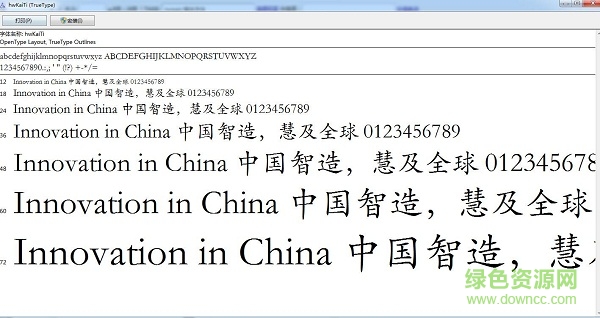
軟件介紹 軟件標簽: hwkaiti 楷體字體 hwkaiti.ttf字體是一款美觀大氣的楷體字體,該字體起筆和收筆分明,結(jié)構(gòu)舒展,柔中帶剛,用于正文排版和包裝設(shè)計,有著不錯的可讀性,歡迎大家前來下載!hwkaiti字體特點這款字體被大量應(yīng)用于報紙、雜志和書籍中的正文,結(jié)構(gòu)秀麗勻稱,筆畫圓潤柔和,可直接用于廣告標語和平面設(shè)計!優(yōu)秀楷體推薦楷體cs-normal普通體 授權(quán):免費軟件 WinAll, WinXP, Win7大小:3.4M語言:中文楷體csregular普通字體是一款規(guī)整大氣的楷書字體,該字體結(jié)構(gòu)瀟灑,筆畫搭配合理,線條流暢大方,雅俗共賞,適用領(lǐng)域廣泛,喜歡的朋友快來下載吧!楷書字體練習(xí)要點掌握好大楷的點畫、結(jié)構(gòu)、布白,做到點畫準確精到下載地址方正小龍楷體ttf 授權(quán):免費軟件 WinAll, WinXP, Win7大?。?.4M語言:中文方正小龍楷體ttf字體是一款端正漂亮的楷書字體,字體線條筆畫流暢,個性鮮明,大氣實用,適用于廣告標語、包裝設(shè)計以及平面設(shè)計等方面,有需要者歡迎下載!創(chuàng)意字體介紹【書同體】在風(fēng)格上有獨到之處,是積幾十年下載地址hwkaiti字體安裝方法方法一:控制面板/字體/文件/安裝新字體;方法二:直接將字體復(fù)制到C:\WINDOWS\Fonts。方法三:針對win7系統(tǒng),用戶只需選中字體右鍵安裝即可。 軟件截圖 上一張下一張(1 / 1) 安裝詳細截圖 猜你喜歡 楷書字體 楷書字體 楷書字體是綠色資源網(wǎng)小編專為大家收集的一類非常流行而且好用的楷書字體,它包括了各種形式的楷書??瑫步姓⒄鏁?、正書。從程邈創(chuàng)立的隸書逐漸演變而來,更趨簡化,橫平豎直,筆勢雄奇,姿態(tài)橫生,可應(yīng)用于繪畫設(shè)計、藝術(shù)創(chuàng)作、平面廣告、印刷包裝、電視廣告等等各行各業(yè)。也是現(xiàn)在很多行業(yè)必用的一類字體,小編收集的這一類楷書字體希望能更好的幫助大家收集和使用楷書字體。 查看更多>> 楷體國標字體官方版 2.45M/中文/7.1/下載 漢儀閃耀楷書字體 1.77M/中文/0.0/下載 華為漢儀錦時楷書 2.92M/中文/5.0/下載 楷書字典手機版 4.46M/中文/5.0/v2.0 安卓版下載 經(jīng)典楷體繁體 3.96M/中文/5.0/下載 楷書繁體字體包 9.76M/中文/8.0/下載 其他版本下載 標題 大小 更新日期 下載 下載地址 電腦版 hwkaiti.ttf 點擊報錯 軟件無法下載或下載后無法使用,請點擊報錯,謝謝! 關(guān)閉報錯反饋 請描述您所遇到的錯誤,我們將盡快予以修正,謝謝! *必填項,請輸入內(nèi)容 本類最新 dreamweaver字體庫 首爾南山體字體 v1.06 官方版 潮字社風(fēng)云簡ttf 潮字社凌渡鯤鵬簡體字體 潮字社曾玉波手書簡字體 微博慧心字體 相關(guān)文章 Apache的ReWrite的應(yīng)用 HostMonitor 網(wǎng)絡(luò)監(jiān)控軟件使用簡單說明 用CMailServer打造郵件服務(wù)器 無需量產(chǎn) UltraISO制作萬能系統(tǒng)安裝U盤 pooworquest partitionmagic 8.0調(diào)整硬盤分區(qū)的方法與步驟 Server Application Unavailable的解決辦法 用戶評論 熱門評論 最新評論 發(fā)表評論 查看所有評論(0) 昵稱: 請不要評論無意義或臟話,我們所有評論會有人工審核. 字數(shù): 0/500 (您的評論需要經(jīng)過審核才能顯示)